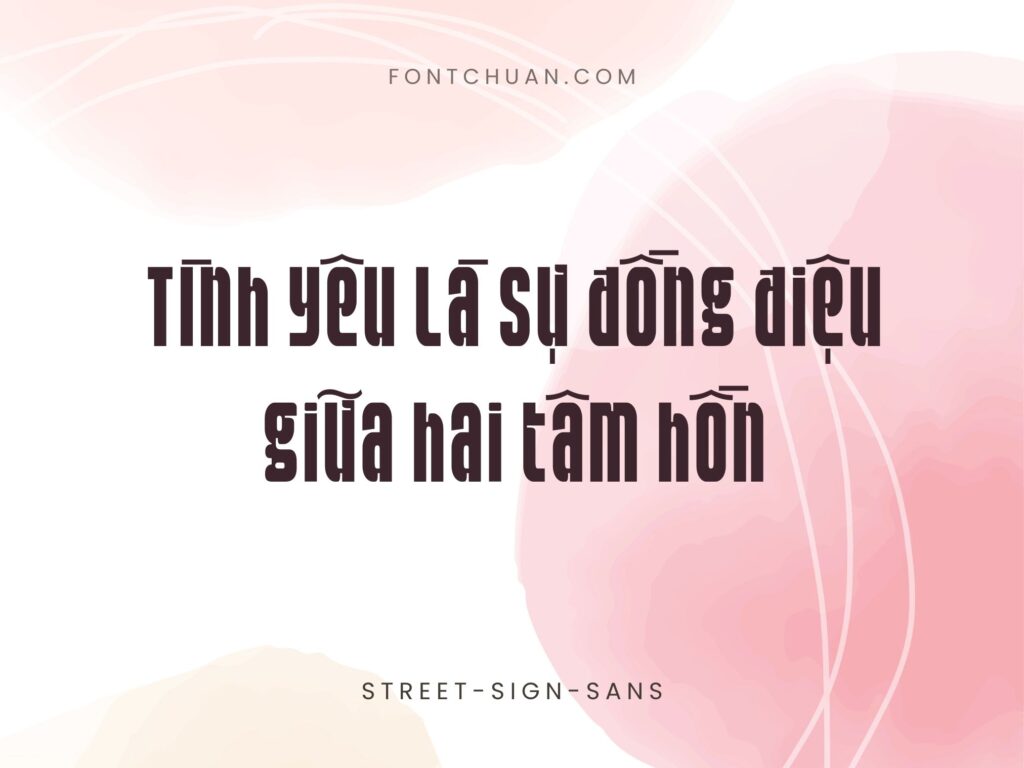
Font Streetsign Sans Font Tiếng Việt
Tác giả Font: Harry Dinh
Streetsign Sans là một font sans-serif đậm, được thiết kế bởi Harry Dinh, lấy cảm hứng từ các biển hiệu vẽ tay tại Việt Nam trong thập niên 80-90. Font này được xây dựng đặc biệt để hỗ trợ tiếng Việt, với các ký tự in hoa đầy cá tính và độc đáo. Phiên bản mới nhất, BD StreetSign Sans v2.0, bao gồm 16 kiểu chữ và một font biến đổi, mang đến sự linh hoạt cho các dự án thiết kế. Font được sưu tầm và đăng bởi thành viên của Font Chuẩn.
Với thiết kế chữ đậm, các đường nét góc cạnh và hình học rõ ràng, Streetsign Sans tạo nên sự nổi bật và dễ đọc. Font này phù hợp cho các thiết kế liên quan đến thương hiệu, tiêu đề, poster và các ấn phẩm truyền thông cần sự mạnh mẽ và hoài cổ. Nhờ tính linh hoạt và hình thức hiện đại, Streetsign Sans còn là một Font chữ công nghệ lý tưởng, giúp thiết kế các sản phẩm số, giao diện ứng dụng, website và tài liệu kỹ thuật trở nên sắc nét, chuyên nghiệp và dễ tiếp nhận.